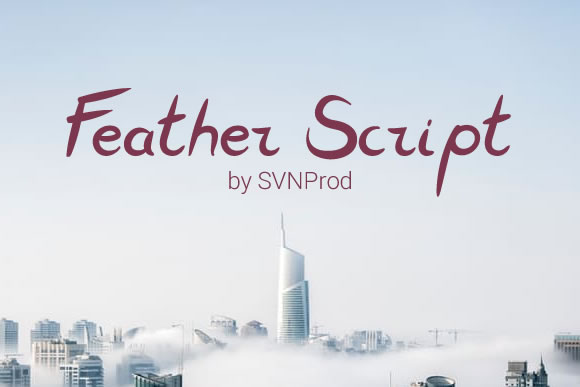
Feather Script
Se stai cercando risorse di alta qualità come Feather Script, questo pacchetto premium è una scelta fantastica per i tuoi progetti creativi.